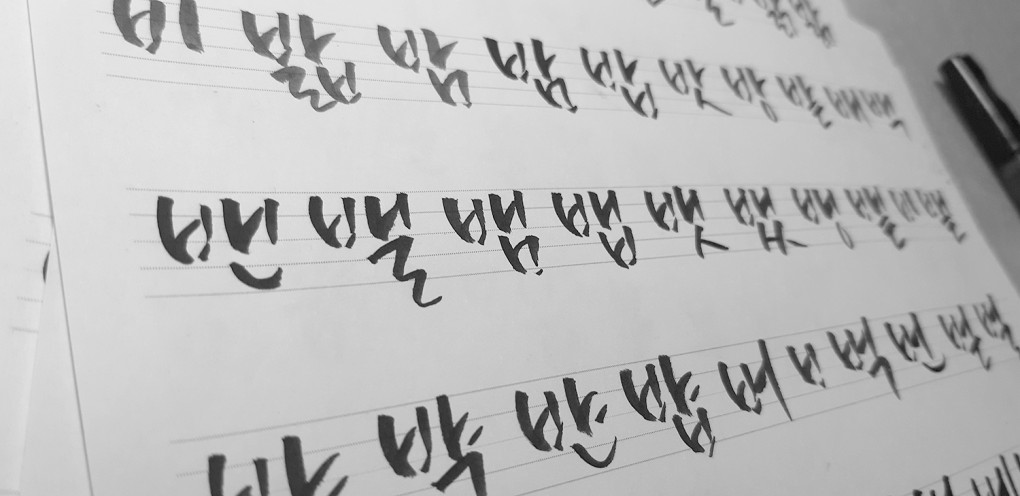
캘리그라피 기반 폰트를 만드는, 진유성 폰트 디자이너
Q. 안녕하세요. 디자이너님, 간단한 소개 부탁드립니다!
안녕하세요. 저는 캘리그라피 작업 기반의 폰트를 만들고 있는 독립 디자이너 진유성입니다. 과거 산돌에 근무하면서는 「Sandoll 칠성조선소」 폰트를 디자인했습니다. 2020년 12월에는 캘리그라피 폰트 「봄눈」을 출시한 이후, 계속해서 새로운 캘리그라피 폰트를 제작하고 있습니다.
Q. 「칠성조선소」도 그렇고「봄눈」도 그렇게 손으로 쓴 글씨가 기반인 폰트를 제작하고 계시는 것 같아요. 폰트 디자인을 시작하게 된 계기가 궁금해요.
작업자 입장에서 캘리그라피 작업은 그 자체가 1회성에 머무는 경향이 있지만 폰트는 한번 만들어 놓으면 무제한으로 활용할 수 있다는 점이 큰 매력으로 느껴졌기 때문에 폰트 디자인에 관심을 갖게 되었습니다. 디자인에 깊이를 더하고자, 건국대학교에서 <만화의 구성적 요소를 반영한 전용 폰트 개발에 관한 연구>라는 논문으로 석사학위를 취득하기도 했죠.
Q. 폰트 디자이너가 되려면 어떤 것들이 필요할까요?
프로젝트를 끝까지 수행할 수 있는 끈기와 지구력이 필요하지 않을까 싶어요. 초기 시안 글자만 만들 때는 디자인 형태가 마냥 재밌고 예뻐 보일 수 있지만, 백, 천 단위가 되었을 땐 생각지 못했던 디자인 이슈들이 계속해서 발생할 수 있거든요. 새로운 이슈들을 해결해 가는 장기전 속에서, 최종 한 벌의 글꼴로 완성할 수 있는 지구력이 폰트 디자인의 핵심인 것 같아요.